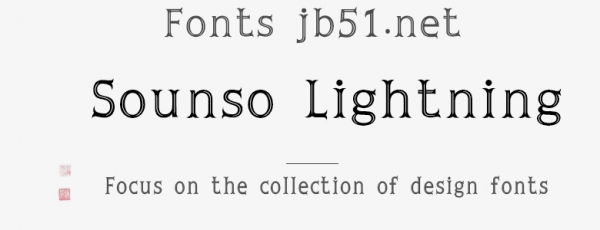
Sounso Lightning是由上首造字出品的英文字體,這款字體字體筆劃細(xì)長,橫豎筆進(jìn)行裝飾,同時(shí)為筆劃做了鏤空設(shè)計(jì),字體整體呈現(xiàn)出浪漫古典的風(fēng)格,適合應(yīng)用于藝術(shù)設(shè)計(jì)、平面宣傳設(shè)計(jì)、網(wǎng)頁設(shè)計(jì),書法字帖等領(lǐng)域。